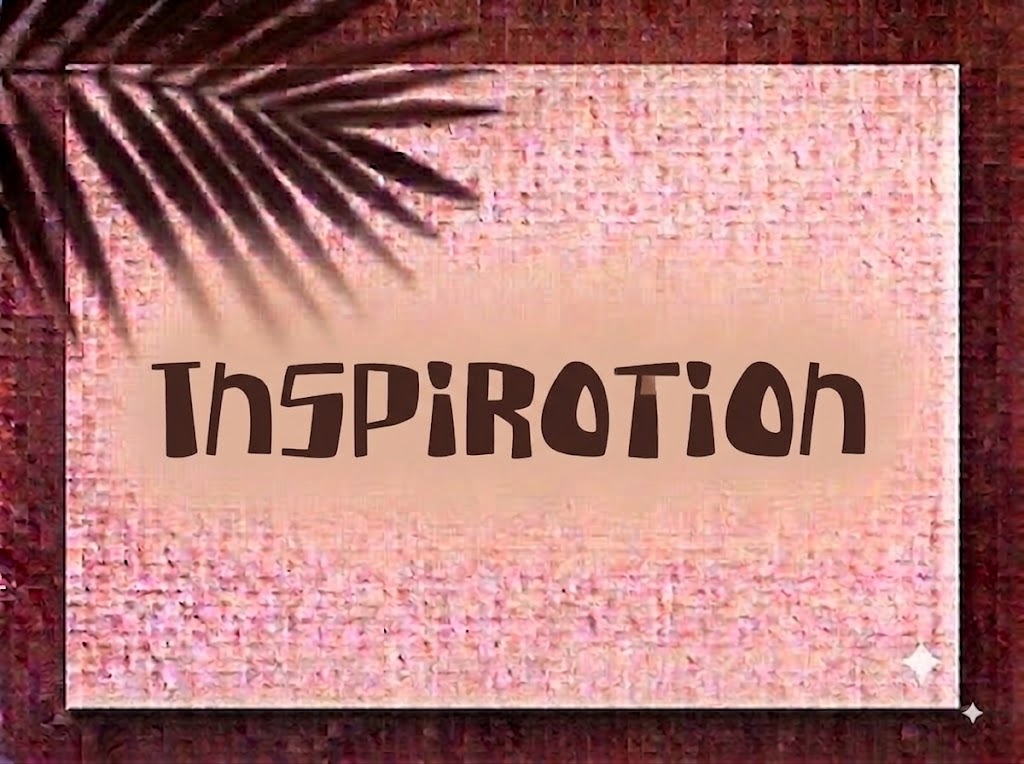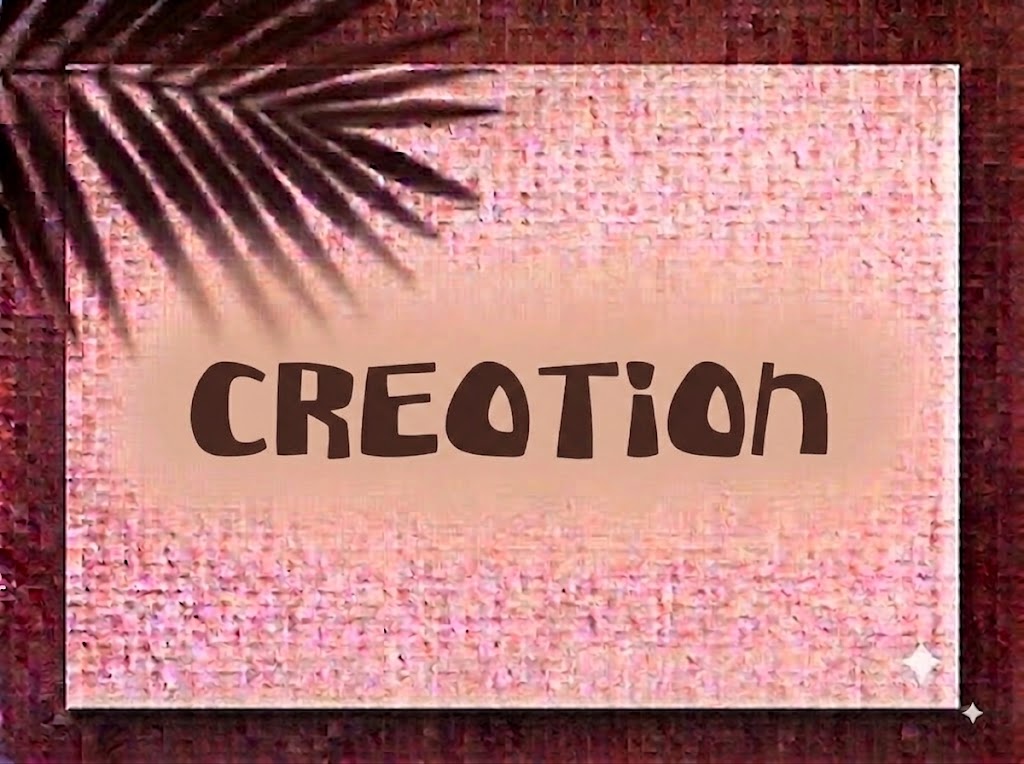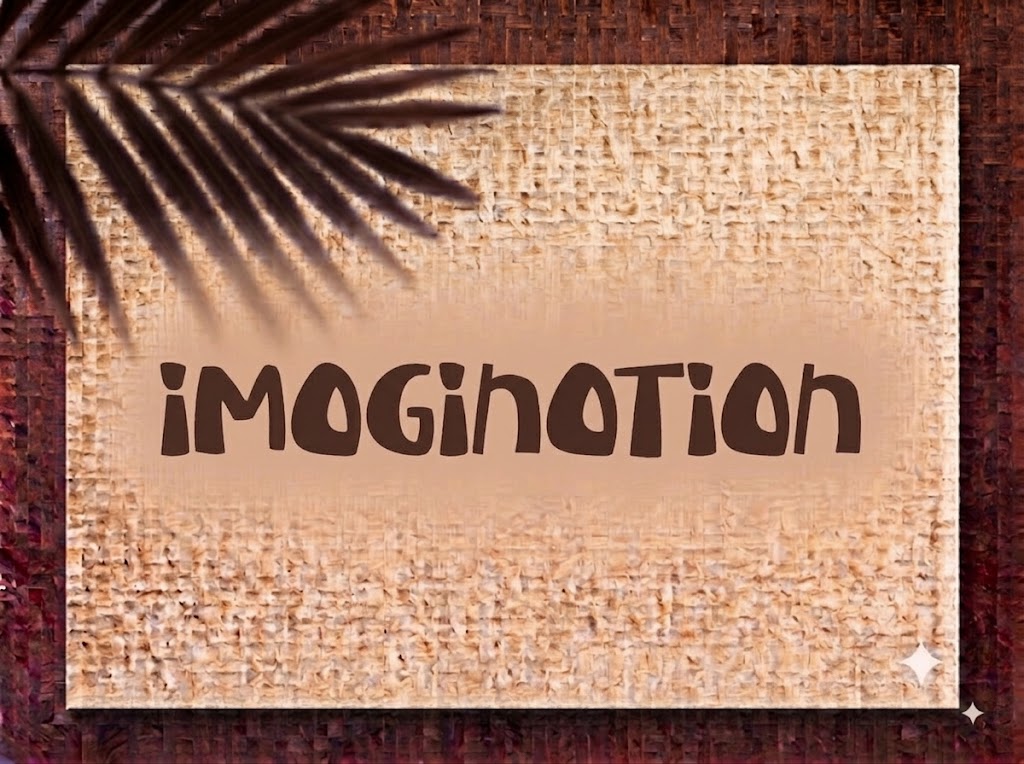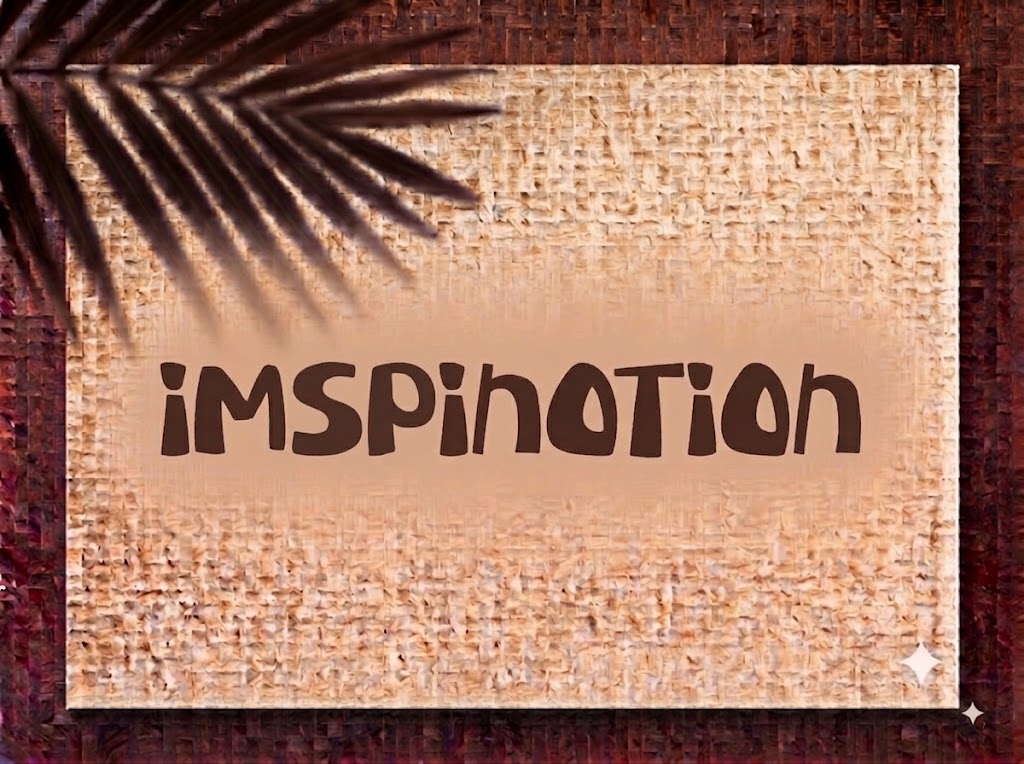
1FTV Randomly
Trong thế giới thiết kế đồ họa truyền thông và sáng tạo nội dung số, xu hướng Cutout (cắt dán thủ công), Ransom Note và phong cách typography bất quy tắc (quirky/doodle) đang tạo nên cơn sốt mạnh mẽ. Những con chữ có phom dáng ngẫu hứng, đường cắt góc cạnh tự do và nhịp điệu nhấp nhô vui nhộn luôn mang lại nguồn năng lượng bùng nổ, hài hước và đậm chất đường phố.
Nếu bạn đang tìm kiếm một phông chữ hiển thị độc lạ, mang tinh thần tự do và phá cách để làm thumbnail YouTube, sticker, áo thun streetwear, poster nhạc indie hay tiêu đề video ngắn Gen Z, font 1FTV Randomly chính là sự lựa chọn không thể bỏ qua.
Giới thiệu về font 1FTV Randomly
Font 1FTV Randomly là bộ chữ hiển thị trang trí (decorative display font) lấy cảm hứng từ nghệ thuật cắt giấy dán ngẫu hứng và nghệ thuật vẽ doodle đường phố:
Tên phông chữ: 1FTV Randomly
Đặc điểm nổi bật của phong cách thiết kế Randomly
Sức hút thị giác của font 1FTV Randomly đến từ tinh thần “bất quy tắc” có chủ đích cùng cấu trúc hình khối đậm nét cá tính:
Tạo hình khối Paper-cut góc cạnh: Mỗi ký tự được tạo tác như những mảnh giấy màu được cắt thủ công bằng kéo, tạo nên các góc cắt xéo sắc sảo và đường viền dứt khoát đầy tính nghịch ngợm.
Đường gióng Baseline & Chiều cao nhấp nhô: Điểm đắt giá nhất của phông chữ nằm ở việc các con chữ không tuân theo một đường chân cố định mà nhảy múa tự do. Sự phối hợp xen kẽ giữa nét to bản và nét mảnh tạo cảm giác nhịp điệu sinh động, tràn đầy năng lượng tươi trẻ.
Cấu trúc chữ đậm (Bold Block) bắt mắt: Nét chữ dày dặn giúp tiêu đề luôn chiếm trọn tâm điểm thị giác, cực kỳ nổi bật ngay cả khi đặt trên các phông nền nhiều chi tiết hoặc chuyển động nhanh.
Khoảng cách giữa các chữ (kerning) và độ giãn dòng được tính toán chuẩn xác, giúp các khối chữ bất quy tắc khi đứng cạnh nhau vẫn giữ được sự liền mạch, không bị rối mắt hay đè chồng lên nhau.
Tích hợp trọn vẹn bộ chữ cái hoa – thường, dãy chữ số 0-9 phom dáng độc lạ cùng hệ thống ký tự đặc biệt, dấu câu thông dụng.
Bản Việt hóa chuẩn chỉnh giúp bạn hoàn toàn yên tâm thiết kế các văn bản tiếng Việt có dấu phức tạp mà không gặp lỗi nhảy font hay mất ký tự.
Hình ảnh demo thực tế của font 1FTV Randomly
Khả năng hiển thị của phông chữ này được tối ưu rất tốt trên nhiều tỷ lệ kích thước khác nhau:
Kích thước nhỏ (12pt – 24pt): Độ đậm của nét chữ giúp các câu ngắn và dãy số vẫn dễ dàng nhận diện trên màn hình di động.
Kích thước lớn (36pt – 72pt): Đây là đất diễn hoàn hảo nhất để 1FTV Randomly phô diễn toàn bộ sự phóng khoáng, góc cạnh và nét tinh nghịch của phong cách cắt dán ngẫu hứng, tạo tác động thị giác bùng nổ cho các dòng headline chính.
Ứng dụng trong thiết kế đồ họa và làm video
Sở hữu nét cá tính độc đáo và tươi vui, font 1FTV Randomly mở ra không gian ứng dụng phong phú:
Video ngắn (TikTok, Reels, Shorts): Dáng chữ nhấp nhô rất thu hút trên khung hình đứng tỷ lệ 9:16. Cực kỳ ăn nhập với các video vlog hài hước, review ăn uống đường phố, thử thách vui nhộn, meme hay clip phong cách Gen Z.
Ảnh thu nhỏ YouTube (Thumbnail): Lựa chọn tuyệt vời cho các kênh Gaming, Reaction, Troll, Khám phá thực tế hoặc Talkshow vui vẻ nhờ khả năng giật tít bắt mắt và kích thích tương tác.
Thời trang Streetwear & Merchandise: Thích hợp in ấn lên áo thun oversize, hoodie, mũ lưỡi trai, tote bag, ốp lưng điện thoại hoặc sticker dán laptop/xe máy.
Thiết kế Poster, Bìa Album & Sự kiện: Hoàn hảo cho các poster nhạc Indie, đêm nhạc acoustic ngoài trời, hội chợ nghệ thuật, sự kiện sinh viên hay truyện tranh (comic).